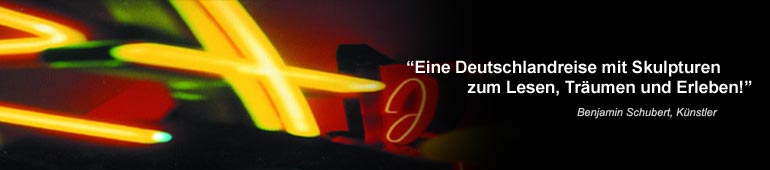
Aktionstag zur Alphabetisierung auf dem Stuttgarter
Marktplatz Der "Corso der Lichtgestalten" macht Station in
Stuttgart
Am Mittwoch, den 18. August 2004 macht der "Corso der
Lichtgestalten" von 10.30 bis 19.30 Uhr Station auf dem Stuttgarter
Marktplatz. Die vom Bundesverband Alphabetisierung e.V. unterstützte
Wanderausstellung weist mit großen, aus Neonbuchstaben gestalteten
Skulpturen des Hamburger Künstlers Benjamin Schubert auf das Problem
des Analphabetismus hin, von dem in Deutschland rund 4 Millionen
Menschen betroffen sind.
Begleitet wird das Kunstprojekt vom ALFA-MOBIL des
Bundesverbandes Alphabetisierung sowie von einem umfangreichen
Informations-, Beratungs- und Kulturprogramm, das von der Mediothek
der Stadtbücherei Stuttgart, der Volkshochschule Stuttgart sowie dem
Stuttgarter Verlag Ernst Klett Sprachen gemeinsam angeboten wird.
Die drei Stuttgarter Institutionen stellen ihre Medien- und
Kursangebote zur Alphabetisierung vor und stehen den ganzen Tag mit
erfahrenen Ansprechpersonen und Gästen für Fragen und Gespräche zur
Verfügung. Anwesend sind u.a. auch die Kalligraphin Claudia Bärbel
Kirsamer und der Geschichtenerzähler Gerald Friese. Auf dem Programm
stehen außerdem ein Buchstaben-Memory von und mit Heinz Spenkuch
sowie ein Straßentheater zum Thema "Kommunikation". Als Höhepunkt
des Aktionstages werden ab 18 Uhr die Neonskulpturen beleuchtet. Um
19.30 Uhr setzt der "Corso der Lichtgestalten" seine Tour durch
Deutschland fort. Sein nächstes Ziel ist Karlsruhe.
Der "Corso der Lichtgestalten" ist der deutsche Beitrag zur
Weltalphabetisierungskampagne der UNESCO und fährt bis Anfang
September zusammen mit dem ALFA-MOBIL des Bundesverbandes
Alphabetisierung e.V. über 30 Städte an. Ziel ist es, über
Analphabetismus in Deutschland zu informieren und Spenden für das
ALFA-TELEFON zu sammeln, bei dem sich "Betroffene" Rat und Hilfe
holen können. Nach Schätzungen des Bundesverbandes Alphabetisierung
e.V. gibt es in Deutschland 4 Millionen funktionale Analphabeten.
Das sind Menschen, die trotz Schulbesuchs so schlecht lesen und
schreiben können, dass sie Probleme bei der Bewältigung des Alltags
haben und kaum in das Berufsleben integriert werden können. Bei den
von Benjamin Schubert gestalteten Skulpturen handelt es sich um
Neonbuchstaben aus ausgemusterten Firmen- und Reklametafeln, die vom
Künstler zu neuen Objekten geformt wurden und verdeutlichen wollen,
wie schwer es für Analphabeten ist, einen Text zu entziffern.